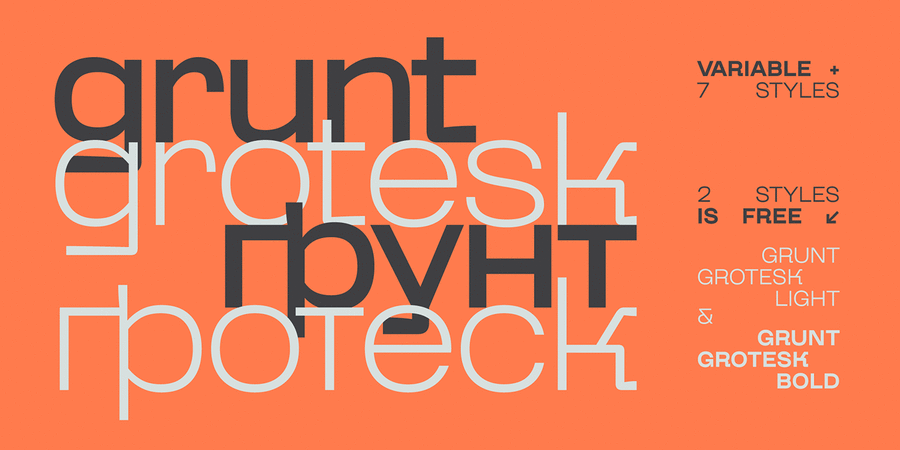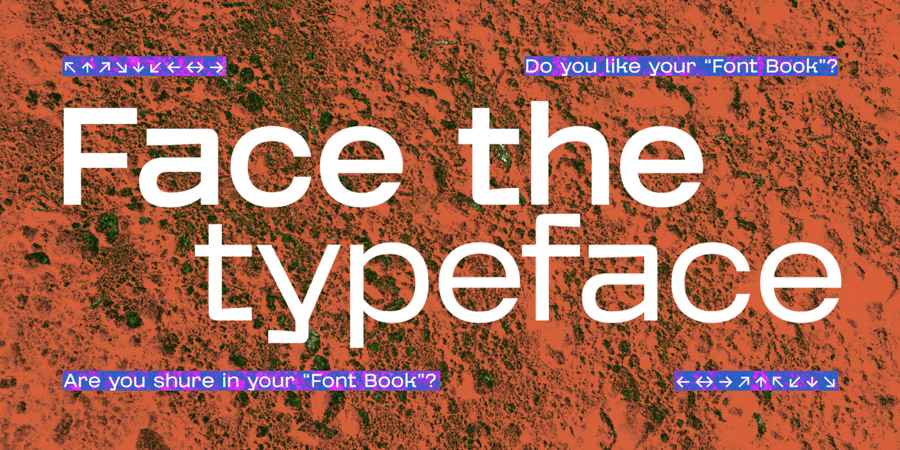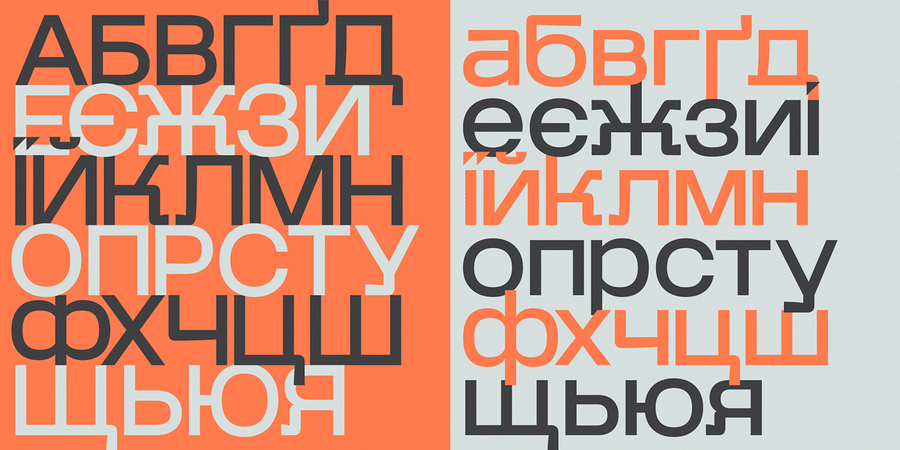
Grunt Grotesk — це сучасний український гротеск з купою красивих деталей, які вирізняють його серед інших шрифтів без засічок, але все ще чудовим у великих масивах тексти. Гарнітура містить 2 безкоштовних накреслення: Grunt Grotesk Light, Grunt Grotesk Bold. Вони доступні за відкритою ліцензією Open Font License (OFL). Шрифт розробив Валентин Ткаченко у 2023 році.
Асоціації з сімейством шрифтів Grunt GroteskОсобистість і характер гарнітури:
точний, рівний, статичний, логічний, стійкий, автоматичний, штучний, інженерний, міський, креслярський, сучасний, тонкий, дротяний, легкий, прохолодний, ясний, модний, неоновий, твердий, надійний, впевнений, сталевий, машинний, космічний, футуристичний, якісний, гострий, ламаний, техногенний, чіткий, урбаністичний, незграбний, дивний, самобутній, оригінальний, характерний, іронічний, грайливий, молодіжний, цікавий, технічний, стабільний, індустріальний, залізний, різкий, комп'ютерний, серйозний, переконливий, сильний, архітектурний, грубий, важкий, авторитетний, значний, мужній, важливий, монументальний, мотивуючий, суворий, крутий, амбітний, практичний, міцний, формальний, солідний, самостійний, відповідальний, добротний, спортивний, військовий, брутальний, гучний, прямокутний, жорсткий, електронний, тусовочний, клубний, двіжняковий, потужний